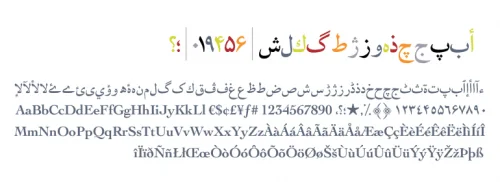
فونت بدر
از سال 1998 تاکنون نسخه های مختلی از فونت بدر برای استفاده در کامپیوتر به صورت رایگان و یا در قالب یک پکیج منتشر شده است. از نسخه ارائه شده توسط شرکت mrt تا نسخه برنا رایانه که متداول ترین آن است. پیش از این فونت بدر را در قالب بسته کامل فونت‌های عربی/فارسی شرکت لاینوتایپ و همچنین دانلود کامل فونت های سری بی B منتشر کرده بودیم. و پیشنهاد کردیم از فونت های لاینوتایپ استفاده کنید چرا که این شرکت اصلی ارائه دهنده فونت است و از استاندارد بالاتری برخوردار است و از حروف عربی نیز پشتیبانی میکند. اخیرا متین صیادزاده نسخه ای اختصاصی خود را از این فونت با نام Badr + را برای انتشار رایگان در اختیار ما قرار داده است. وی این فونت را اینگونه معرفی کرد:
این فونت رو من از پایه فونت بدر ساختم. بعضی حروف فارسی رو بهش اضافه کردم، فاصله گذاری‌هاش رو خیلی اصلاح کردم. برای لیکچرهاش هم از فونت‌هایی مثل Arabic typesetting استفاده کردم.
فونت بدر
فونت بدر در دو وزن نازک و ضخیم (Badr light و Badr bold) با سبک سنتی-عربی و برپایه خط نسخ برای حروف متن توسط عثمان حسینی در سال 1970 طراحی گردید. و توسط شرکت لاینوتایپ ارائه شد.